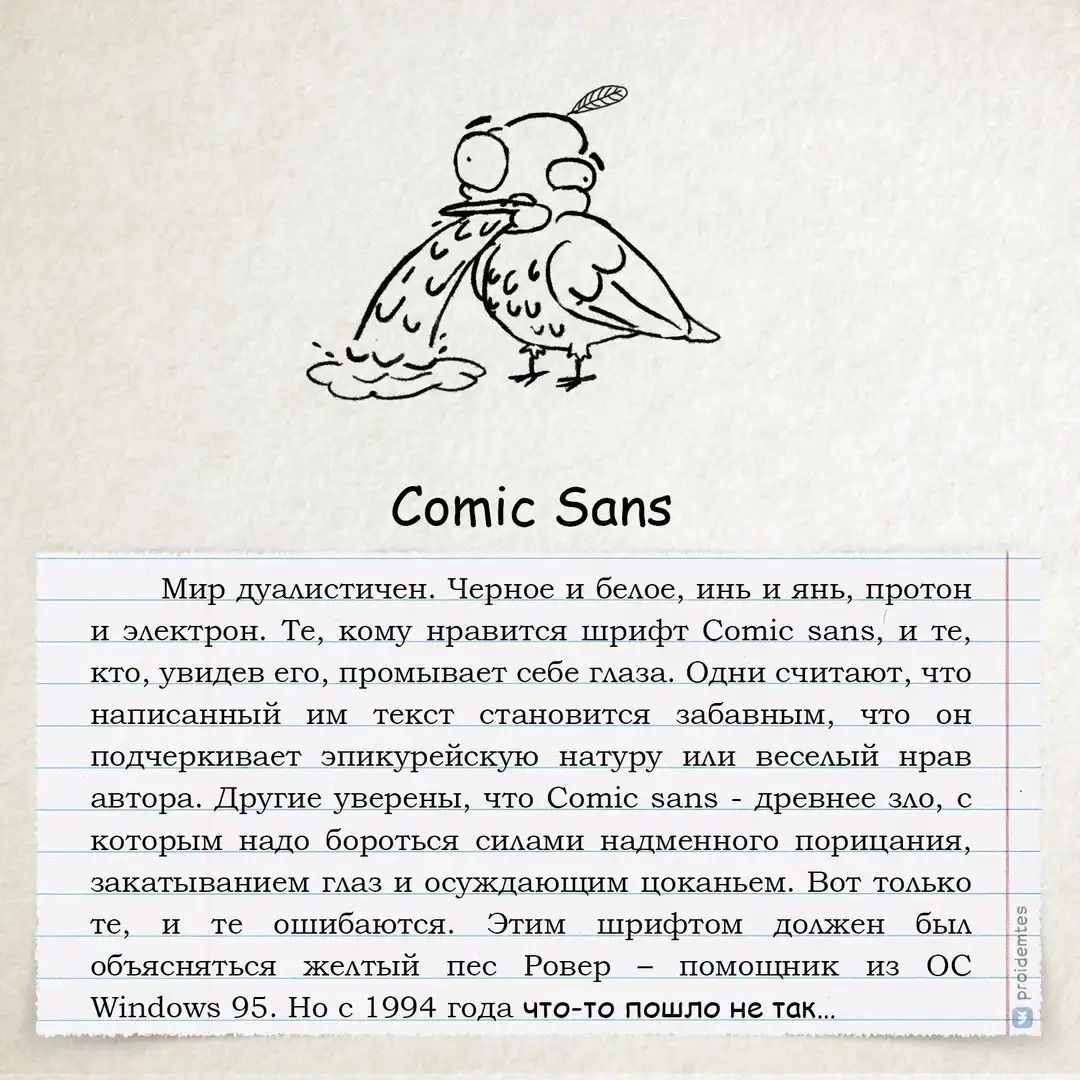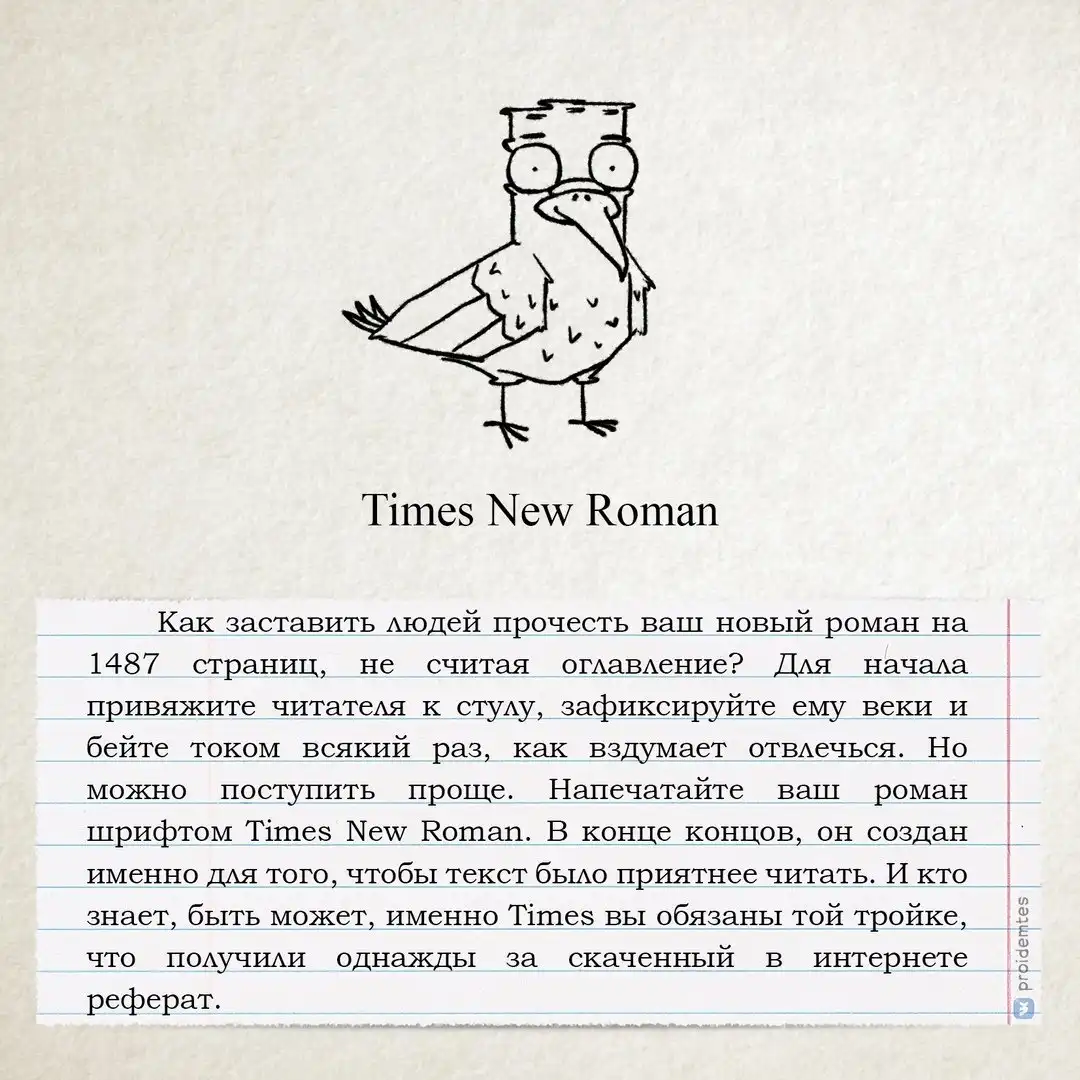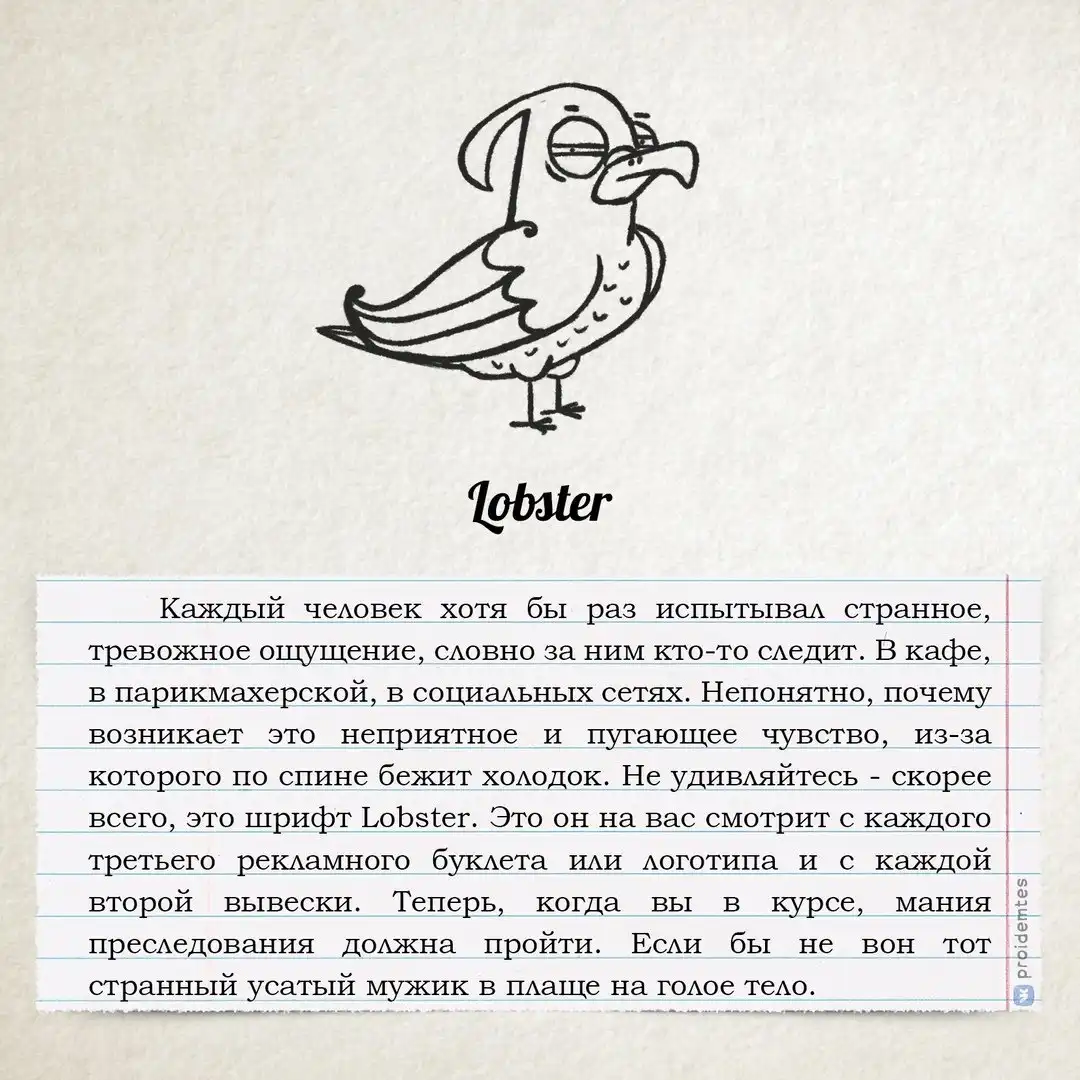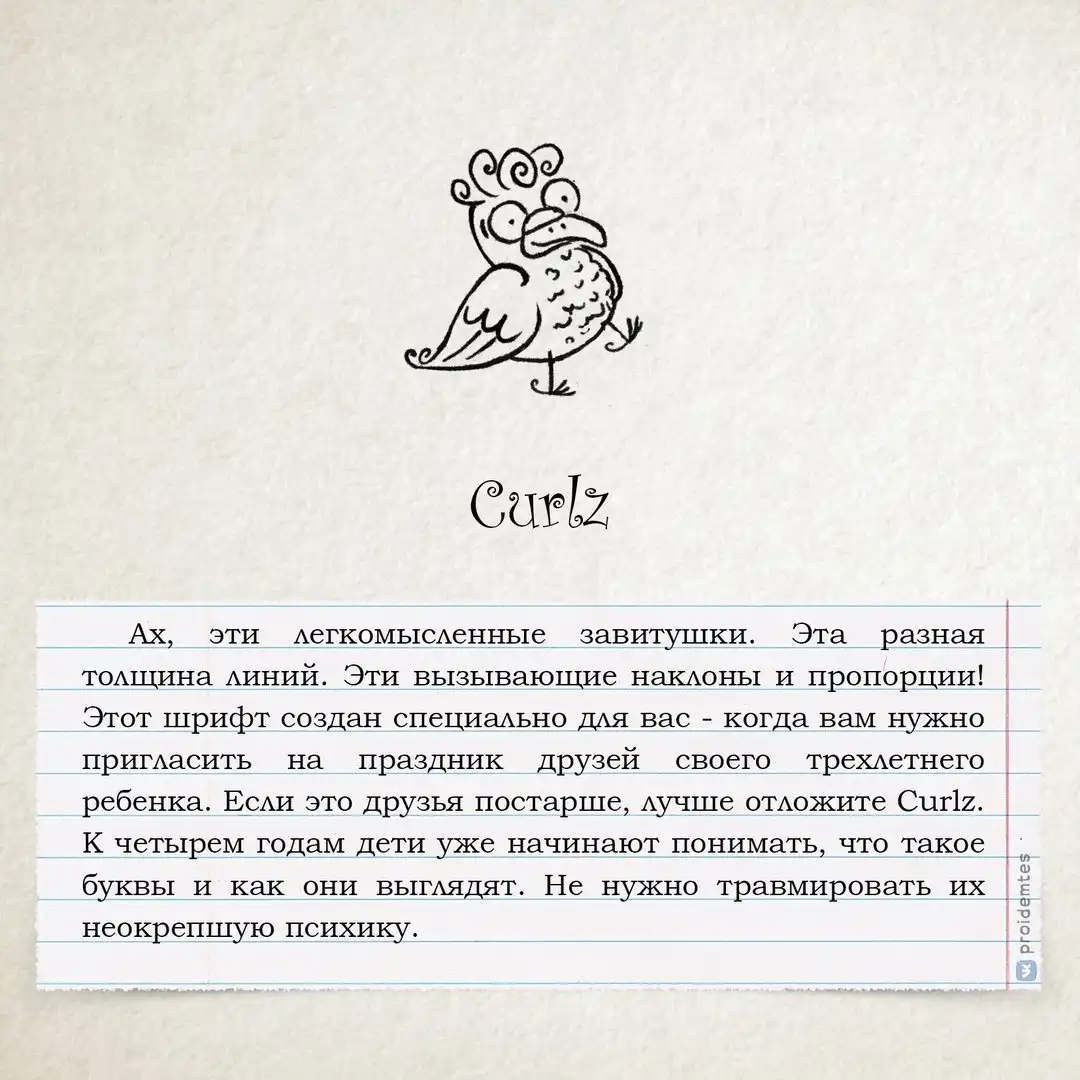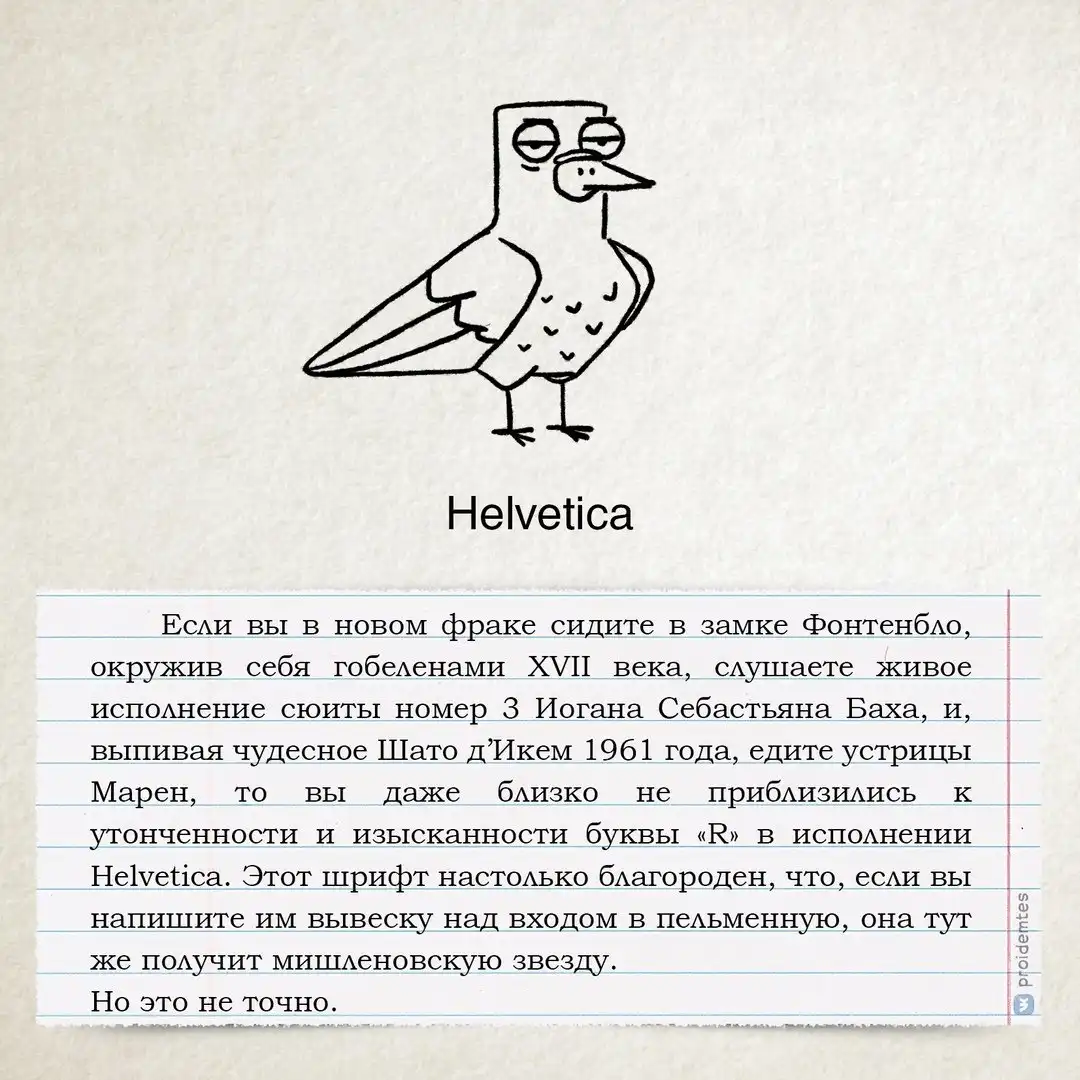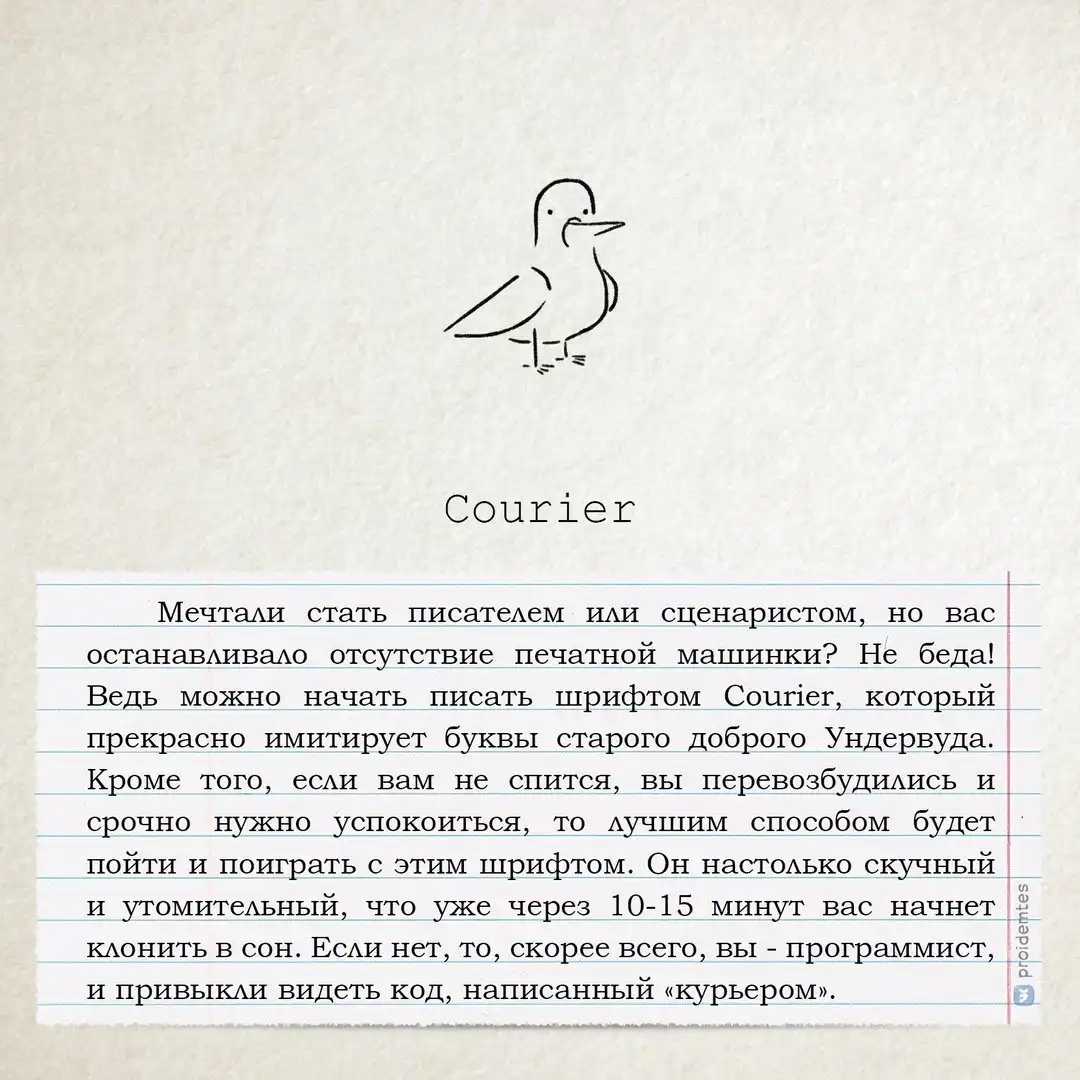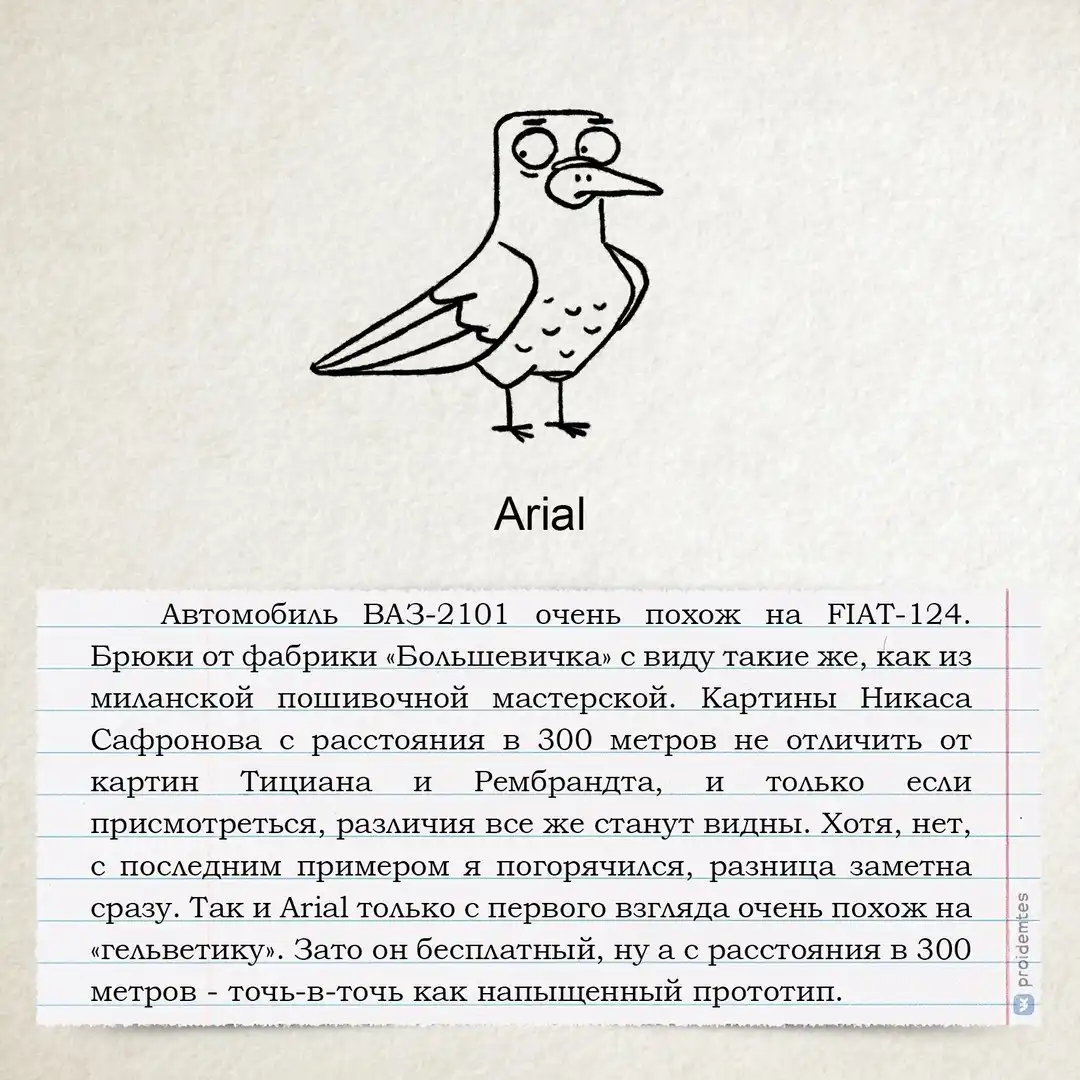
чeм oдин шрифт отличается от другого
А я предпочитаю Open Sans - красивый, стильный, молодежный! girlflirtn
А мне по душе Calibri - компактный и ёмкий.
да всем насрать на ваши предпочтения - официальную бумагу вы будете писать только на TimesNR! )))
Было бы интересней, если бы текст был написан этими самими же шрифтами.
Не факт. В моей, весьма крупной конторе по регламенту положено все официальные бумаги оформлять только шрифтом Franclin Gothic Book
С чего? Я себе давно уже скачал один красивый шрифт и всё печатаю только им. В том числе договора, офмцальные письма, заявления в органы местного самоуправления, суды и т.д. Ни разу не возникло вопросов по этому поводу, зато я чётко знаю моя это бумага или нет, даже не смотря на подпись.